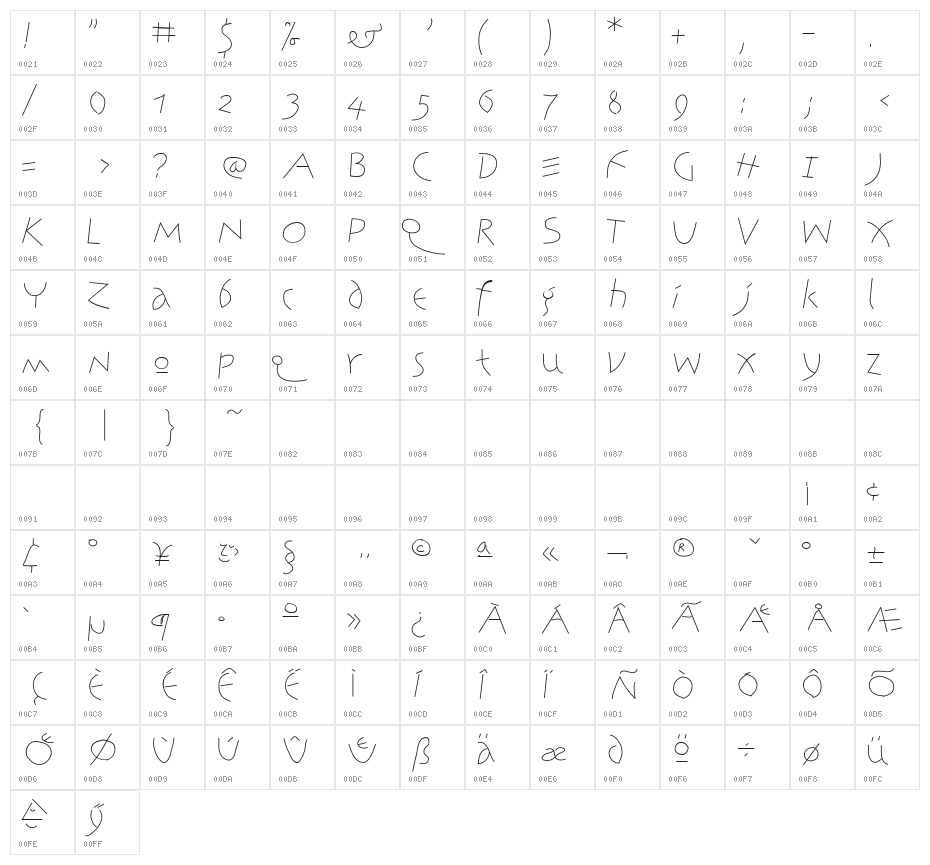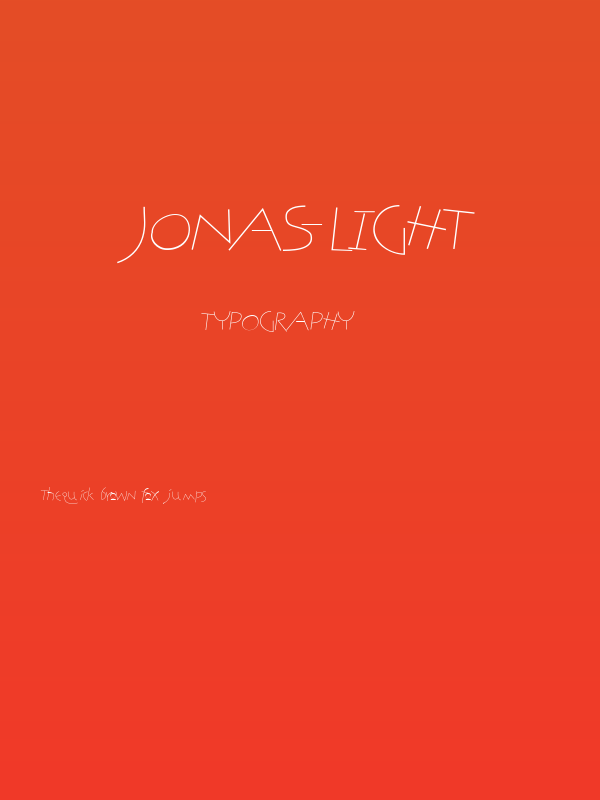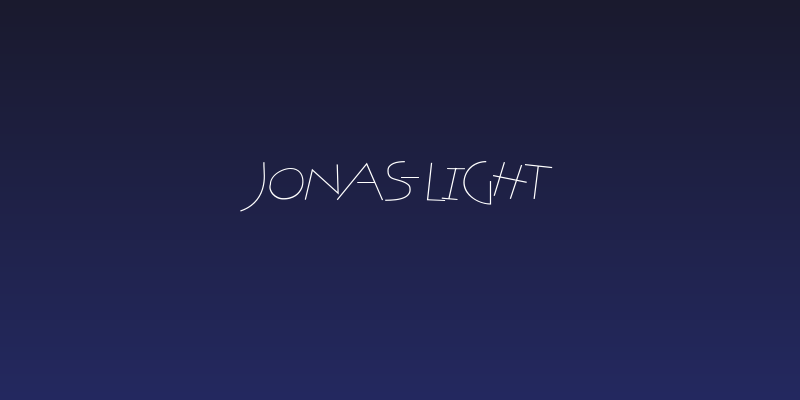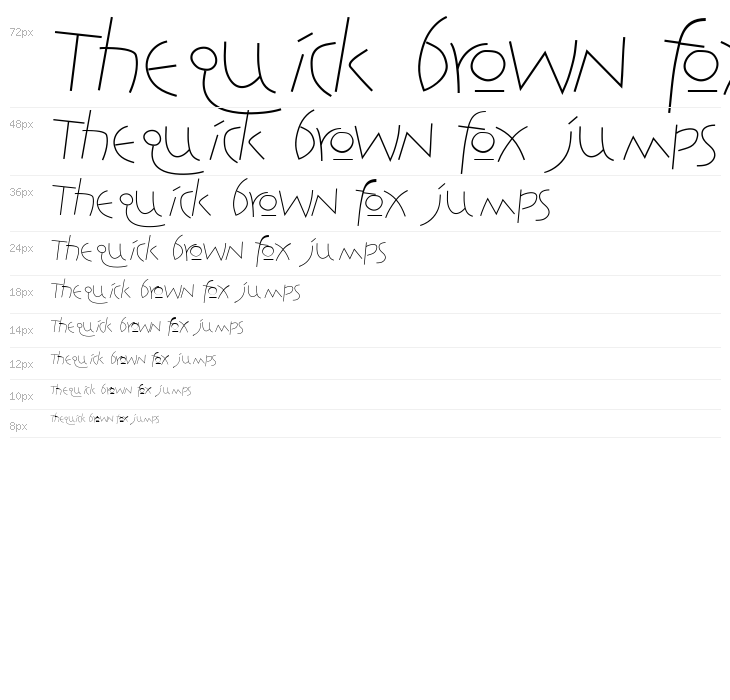
Jonas-Light Font
| Caso d'uso | Logos, Artistic posters, Greeting cards |
| Progetti proposti | Ideal for creative projects such as greeting cards, invitations, artistic posters, and branding materials that require a personal touch. |